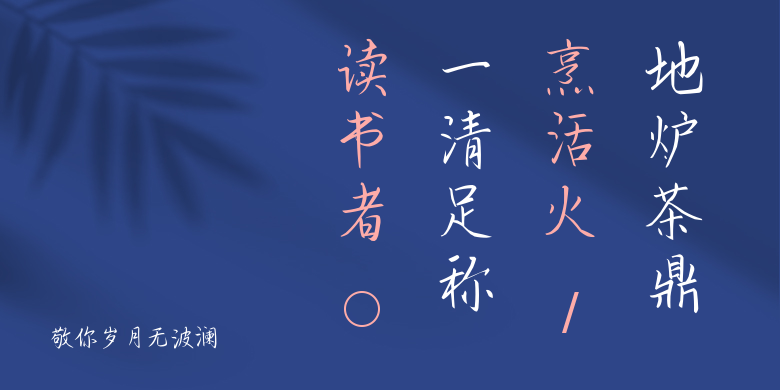
敬你岁月无波澜
敬你岁月无波澜,这款字体结构工整、笔画清晰,兼顾美观与易读性,适用于标题、正文、海报、包装、LOGO 等多种场景。字形优雅稳定,风格百搭耐看,适配日常排版与创意设计,让文字呈现更舒适、更具质感。敬你岁月无波澜一笔一画,皆是细节,以均衡的比例、流畅的线条打造舒适视觉体验,字形端正大气,风格简约现代。无论是商业设计、品牌宣传还是日常排版,都能轻松驾驭,让文字更有格调与力量。敬你岁月无波澜字体下载。